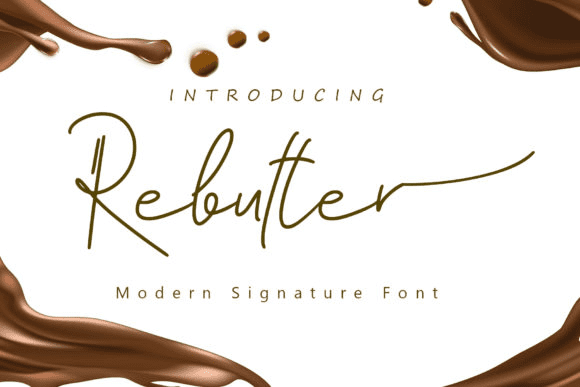
Название: Rebutter Font
Rebutter - это красивый и модный рукописный шрифт с уникальным ощущением и потрясающим эффектом.
Он добавит роскошной искры в любой дизайн-проект, который вы хотите создать!
Название: Rebutter Font
Rebutter - это красивый и модный рукописный шрифт с уникальным ощущением и потрясающим эффектом.
Он добавит роскошной искры в любой дизайн-проект, который вы хотите создать!